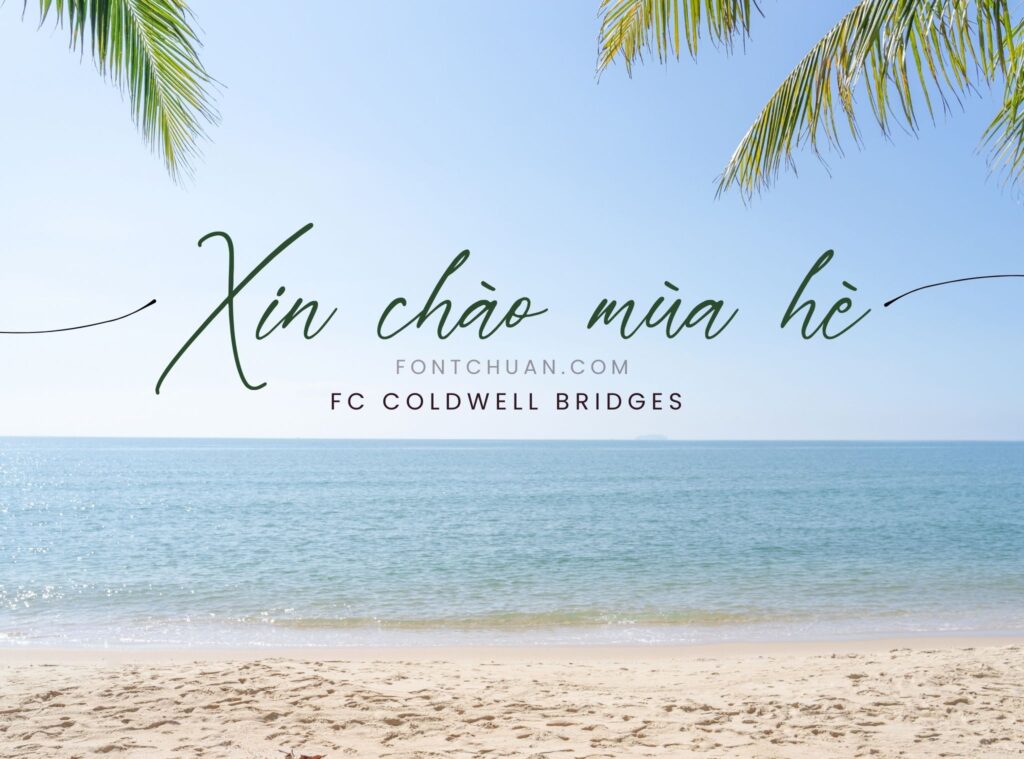
Font FC Coldwell Bridges Việt Hóa
Coldwell Bridges là một font chữ ký tay tinh tế và thanh lịch, được thiết kế bởi Glorytype Studio. Font này mang đến vẻ đẹp mềm mại và cân đối, đồng thời có thể được sử dụng như một Font Lễ hội để tạo điểm nhấn ấm cúng và vui tươi trong các ấn phẩm sự kiện, thiệp mời hay poster đặc biệt. Ngoài ra, nếu bạn muốn một lựa chọn mang phong cách hiện đại và trẻ trung hơn cho mùa lễ hội, font chữ Giáng Sinh cũng là gợi ý lý tưởng để kết hợp với Coldwell Bridges, mang đến sự đa dạng và sinh động cho dự án thiết kế.
Phiên bản FC Coldwell Bridges được Font Chuẩn thực hiện việt hóa VIP thế hệ mới, nhằm hỗ trợ tiếng Việt và nhu cầu sử dụng font miễn phí, giúp cộng đồng thiết kế Việt Nam dễ dàng ứng dụng trong các dự án sáng tạo.
Về đặc điểm thiết kế, FC Coldwell Bridges sở hữu các đường nét uyển chuyển, độ dày vừa phải và hỗ trợ đa ngôn ngữ, lý tưởng và phù hợp cho thiết kế liên quan đến thương hiệu, thiệp mời, thiết kế nội thất, bao bì sản phẩm, cốc, trích dẫn, poster, túi mua sắm, áo thun, bìa sách, thiệp mời và nhiều ứng dụng khác.